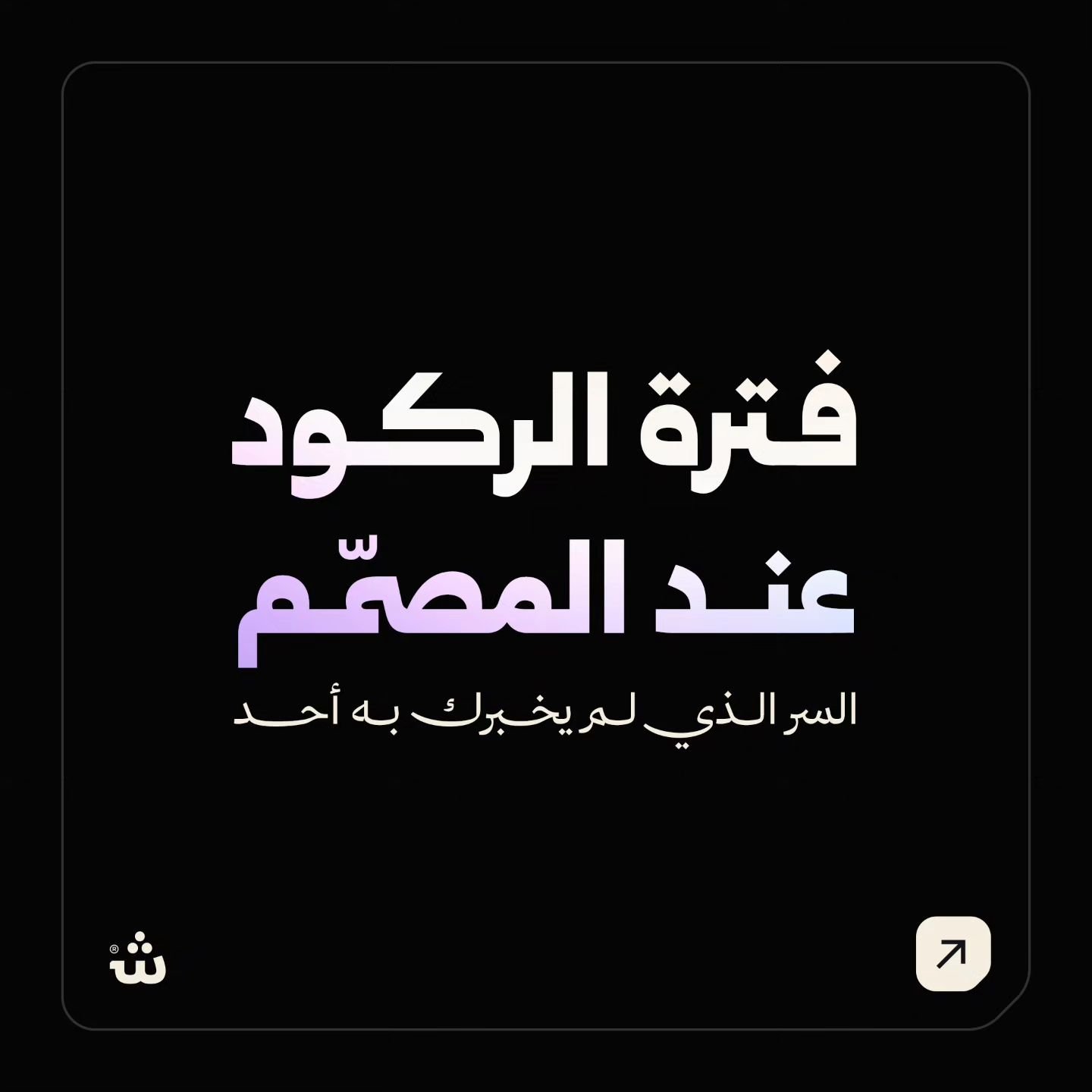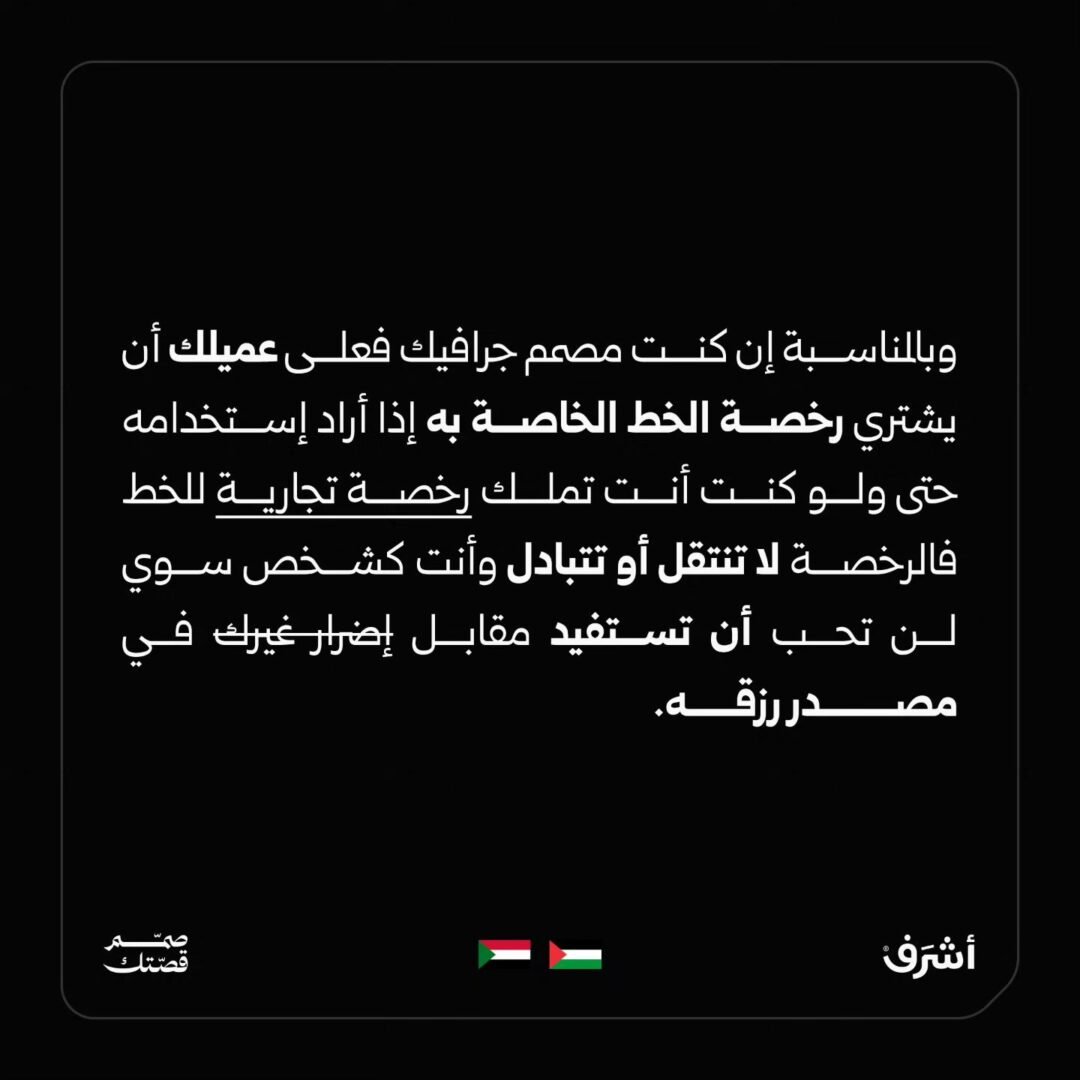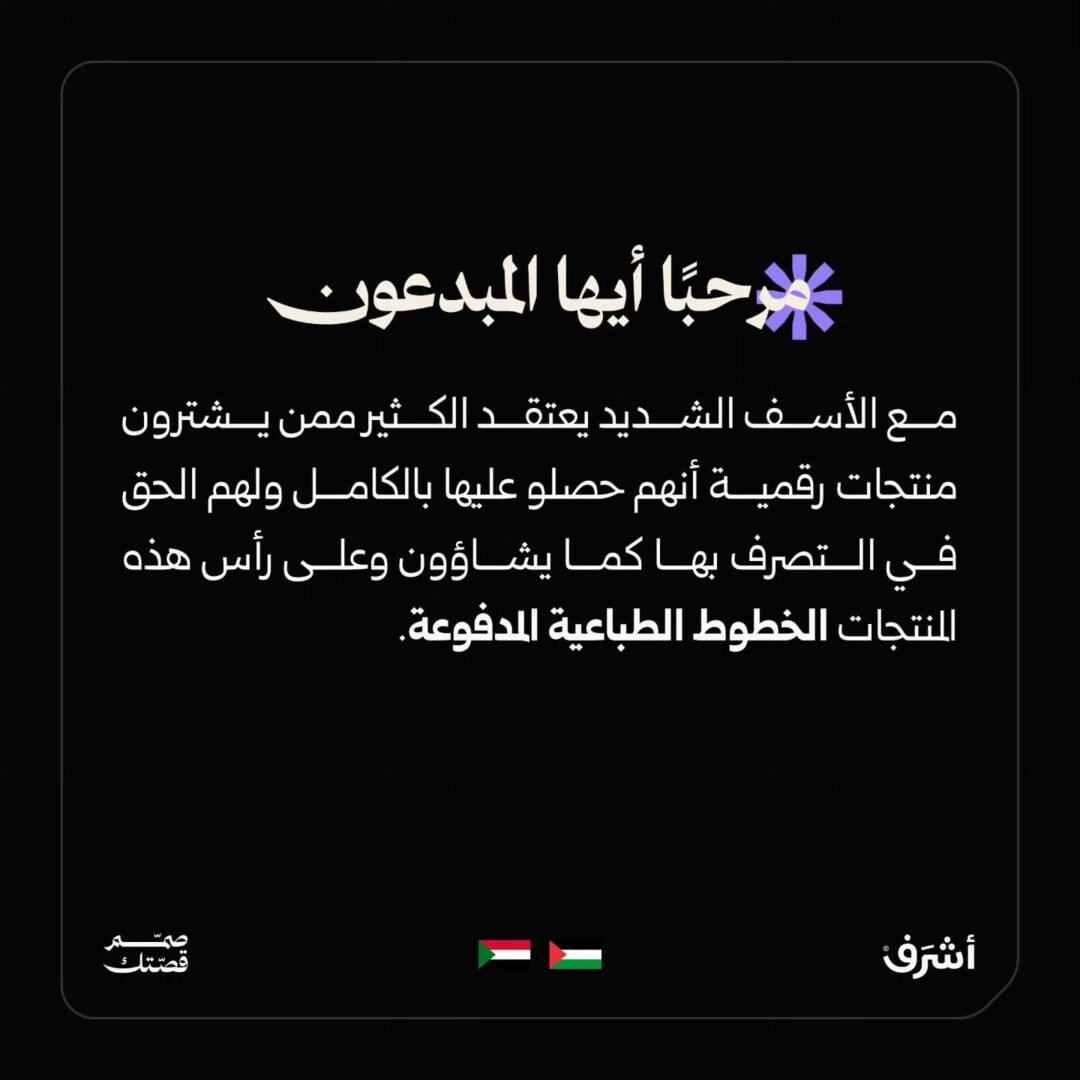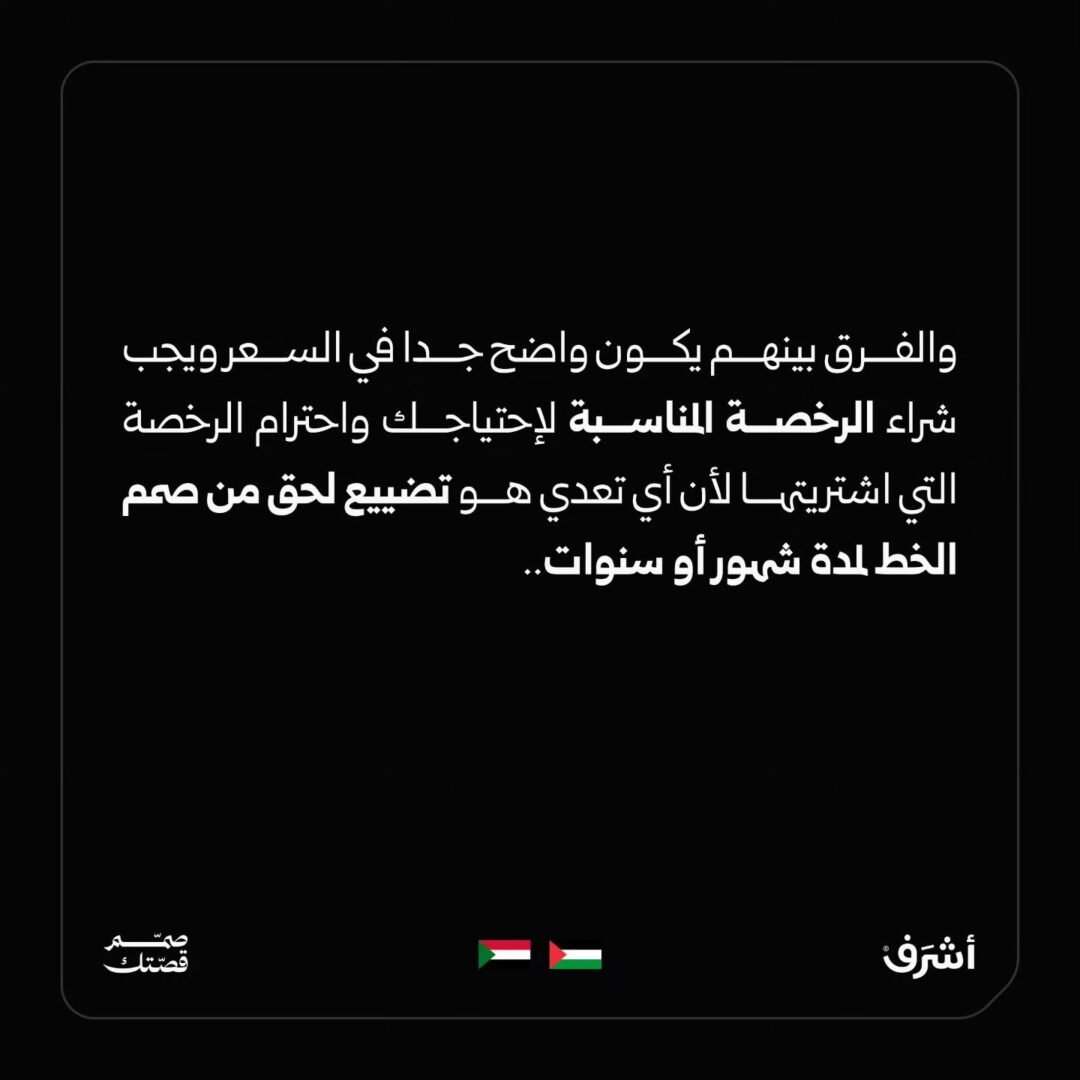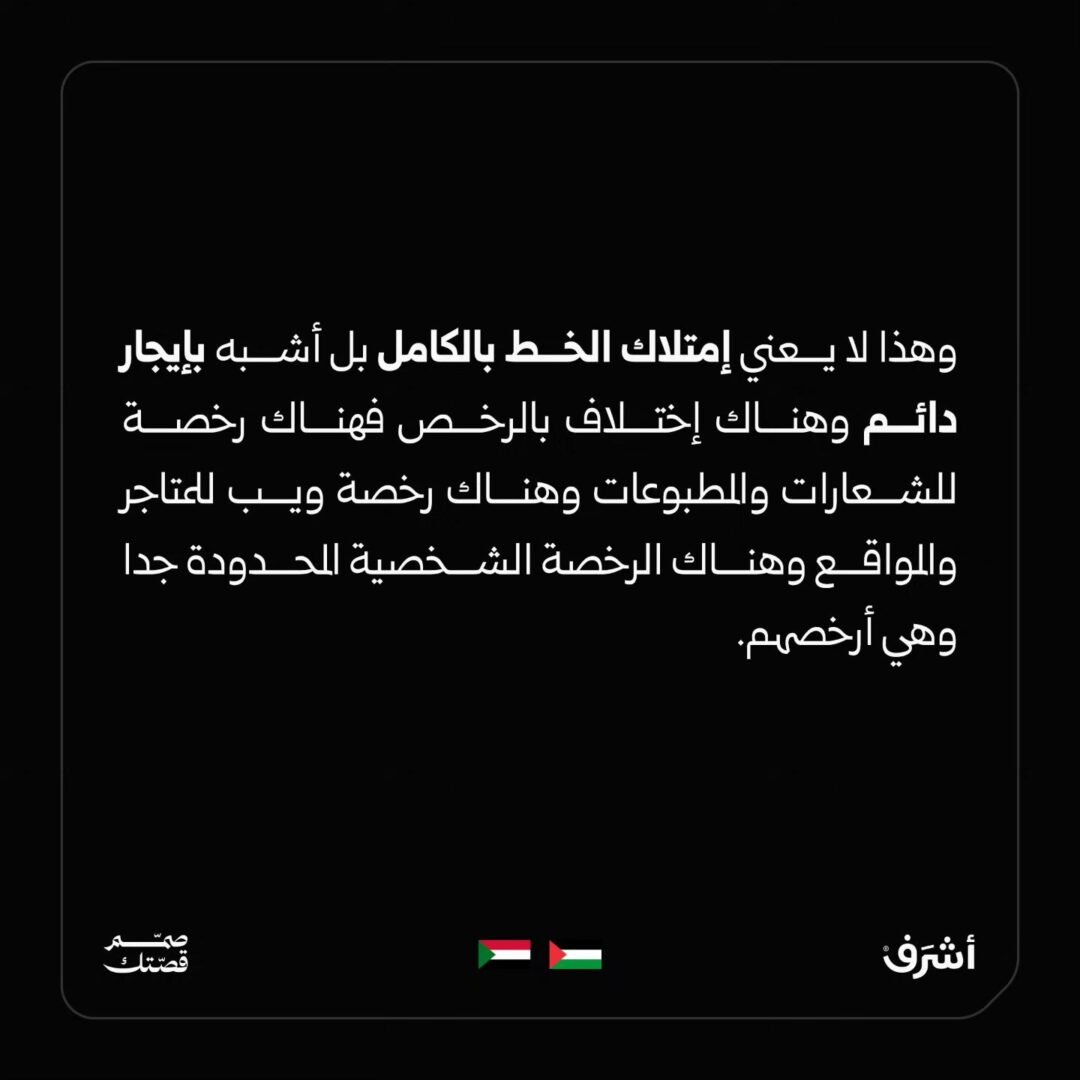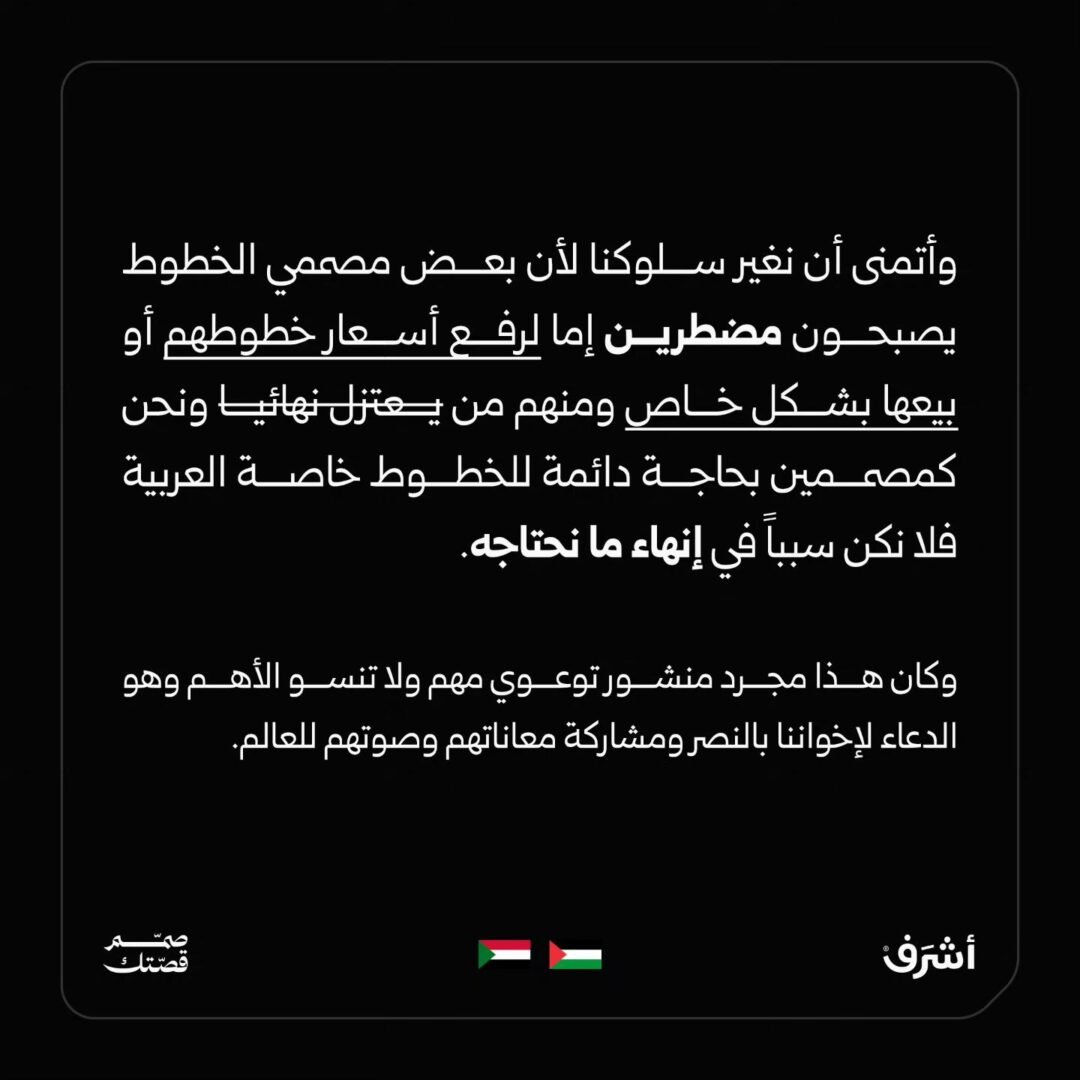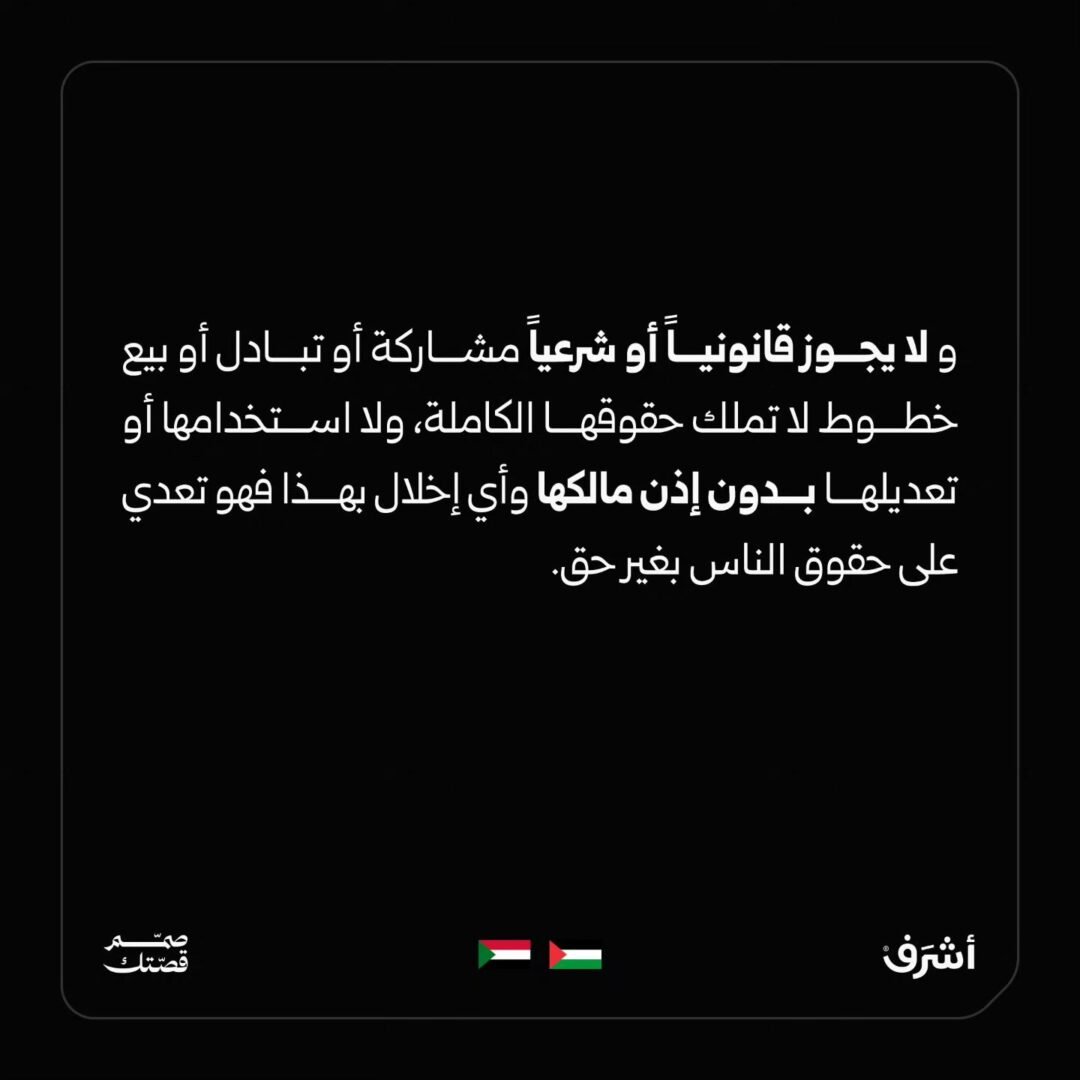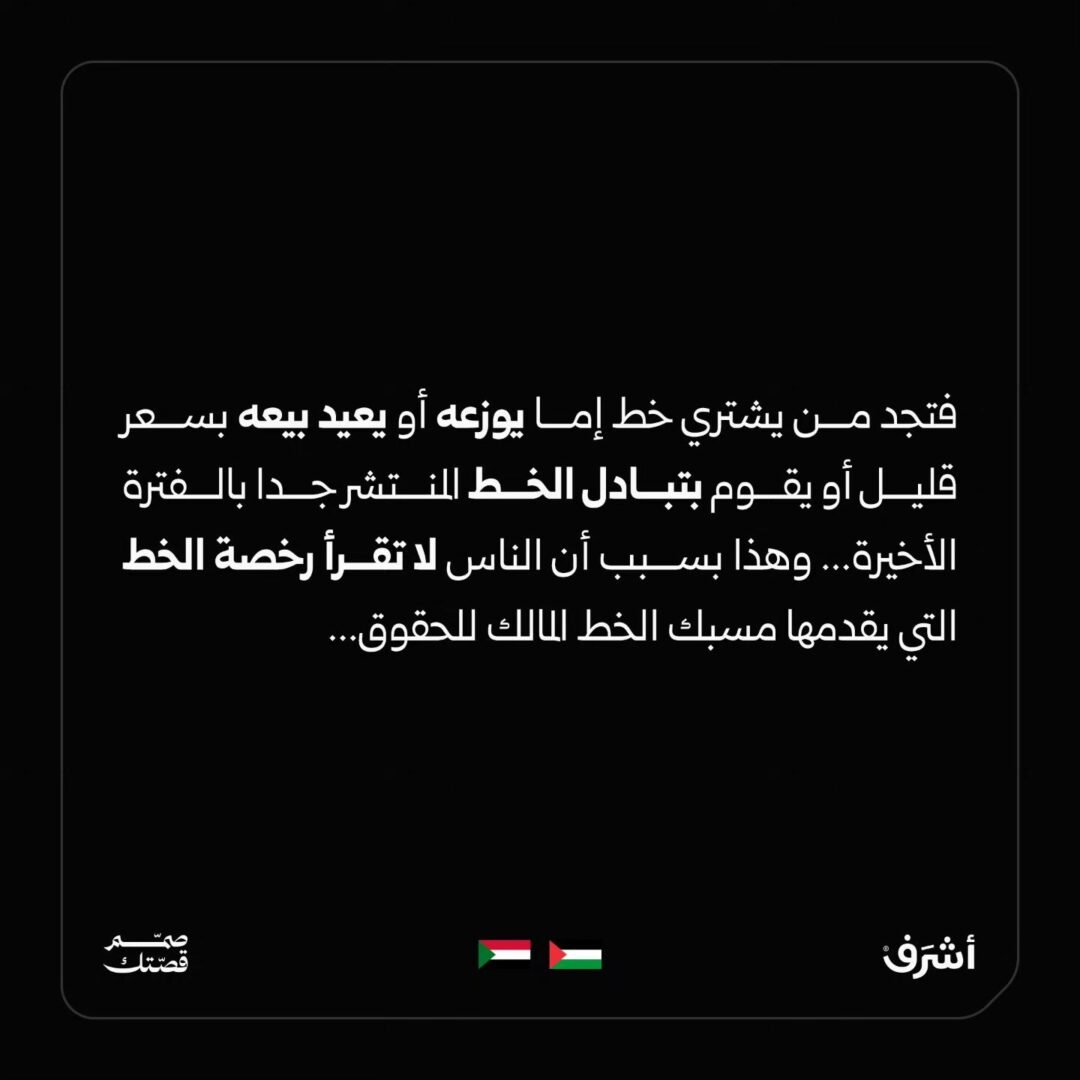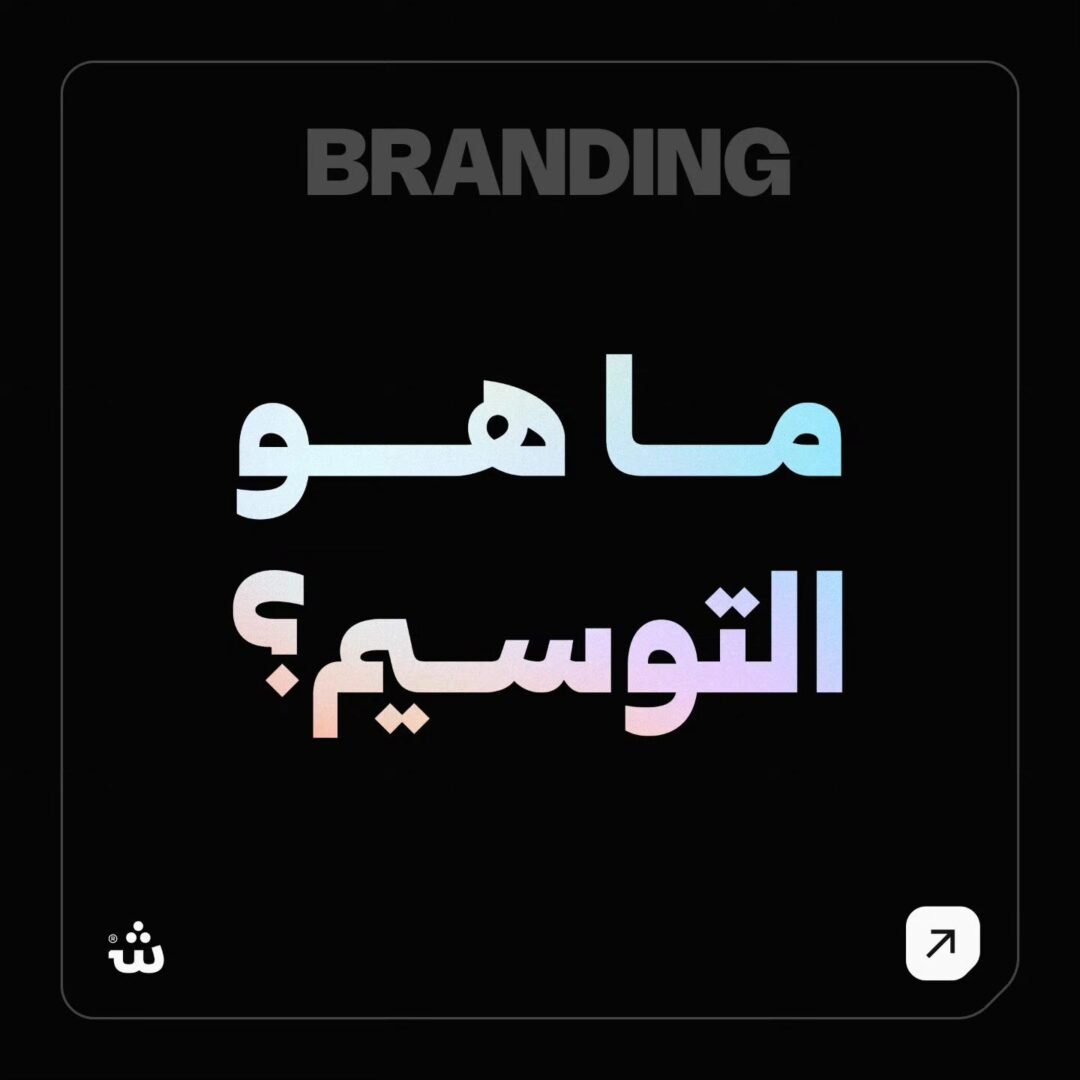
هو خط عربي فريد ومتميز، مستوحى من خط النسخ،يتميز بتصميم بسيط وانيق. ويمكن استخدامه في تصميم الجرافيك، والكتابة المطبوعة، والويب، والتطبيقات المحمولة.
مميزات خط غروب الطباعي:
توافر الأوزان: يأتي خط غروب الطباعي بخمسة أوزان مختلفة.
تصميم بسيط وأنيق: يجمع الخط بين البساطة والجمالية التقليدية لخط النسخ، مما يجعله مناسبًا لمختلف أنواع التصميمات.
مزايـا OpenType: يتضمن الخط العديد من مزايا OpenType التي تضفي عليه مرونة وتنوعًا في الاستخدام، مثل:
الحروف المرسلة: لمسة تقليدية تضفي على النصوص جمالية خاصة.
حرف ياء بنزول أقل: يقلل من نزول السطر، مما يعزز من انتظام النصوص.
النقطة المستطيلة البديلة: توفر تنوعًا وجاذبية بصرية إضافية للنصوص.
الحروف المركبة: تسهم في تحسين المظهر العام للنص وتزيد من سلاسته.